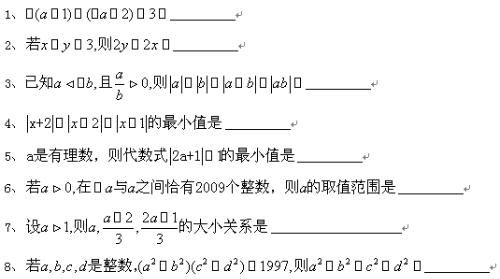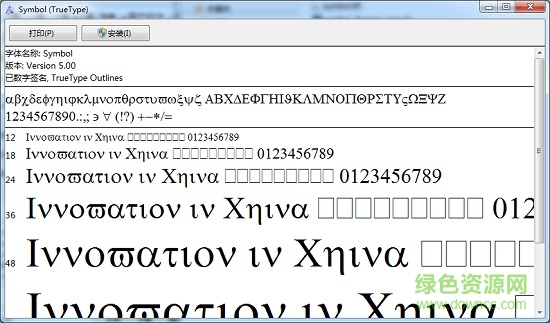
symbol.ttf是一款非常好用的數(shù)學字體,有時候我們在使用一些電腦軟件出現(xiàn)數(shù)學公式亂碼,就是因為缺少了該字體而不能正常的顯示,歡迎有需要的朋友到綠色資源網(wǎng)下載使用!
office數(shù)學公式亂碼解決方案字體
文件不大,卻可以解決你OFFICE里面數(shù)學公式亂碼問題。
有時候我們的word文檔無法正確顯示公式,公式中的一些符號出現(xiàn)亂碼(如下圖),這是因為word中缺少一個symbol.ttf文件